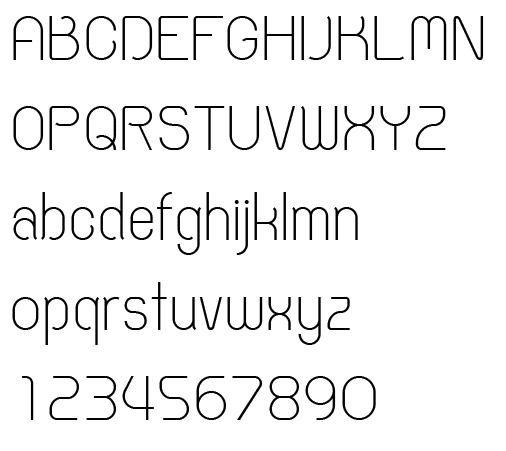
ทีไอ_เทกซ์ ~
พวก สระ วรรณยุกต์ ไม่ไต่คู้ ฯ
เล็กไปมั๊ยครับ อิ อี อึ อื ด้วยครับ
ลองดูนะครับ
(ศิษย์ทำฟอนต์สไตล์เดียวกับอาจารย์เลย สงสัยอาจารย์เอกจะเป็นไอดอล)
เคาะตัวไทยเพิ่ม + เลขไทย  :52:
แล้วก็ตัวภาษาอังกฤษ
คิดอยู่ไม่รู้จะเริ่มยังไงดี คงของเดิมไว้จะดีรึเปล่า ( เพราะว่าแต่เดิมมันก็เป็นตัวเก่าเอามาใส่หัวเฉยๆ )
ตอนนี้เลยแค่ใส่ให้อารมณ์มันเข้ากับตัวไทยเท่านั้นครับ
เลข ๓ กับ ๗ นี่
มันหลุดออกจากพวกหัวขยักเหมือนกันไปหรือเปล่าครับ
แบบพวก พ ฟ ผ ฝ (หรือ m / w) เนี่ยมันมีขีดกลางอยู่ตรงกลางพอดี
ต่างจาก ๓ กับ ๗ ที่ชิดไปข้างนึง
หางเลข ๗ กับ เลข ๙ มันดูแล้วรู้สึก แข็งอ่ะครับ
หลุดจากภาพรวมอ่ะครับ จากความรู้สึก
เลขไทยครับ แก้ตามที่แนะนำ
แล้วก็ Eng สรุปว่าจะไม่แก้ครับ เติมนิดๆหน่อยๆ เอาให้เข้ากับชุดไทย
( แก้ metric เลข 1 เลขน้อย )
เห็นสัดส่วนเลขไทยแบบนี้แล้วไม่ค่อยชินตาเนอะ
จะบอกว่าเราเห็นแต่สัดส่้วนเลขไทยมาตรฐานไงครับ ไม่ค่อยมีไอ้แบบแหวกๆ โผล่มา
พอมีแบบที่มีดีไซน์มาก็เลยแปลกตา
แต่ส่วนตัวก็โอเคนะ ติดแค่บางตัวอย่าง ๓ หรือ ๗
ที่มันจัดพื้นที่อากาศภายในตัวเนื้อของมันไม่ค่อยคล่องเท่าไหร่ (พยายามหาวิธีอธิบายได้แค่นี้)
นอกนั้นก็โอเคแล้วล่ะ แปลกตาดี